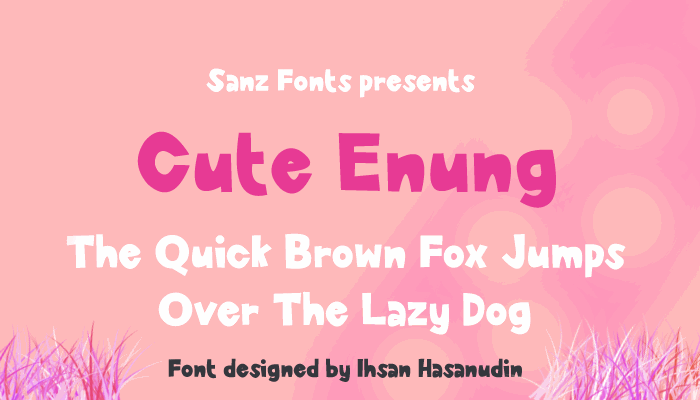
Cute Enung font – Download Grátis
A fonte “Cute Enung” é uma escolha perfeita para quem busca algo autêntico e único, que transmite alegria através do design. Inspirada no mundo encantado dos pequenos pássaros enung, essa display font traz um toque delicado e vivaz ao seu trabalho de design. A elegância natural dos pássaros enung é capturada em cada letra, proporcionando uma experiência visual que se conecta diretamente à natureza do Brasil. Esta fonte foi criada pelo designer Hamilton, e sua beleza surge da combinação perfeita de linhas curvas e traços suaves. Ela funciona maravilhosamente para nomes de marca ou produtos relacionados ao mundo infantil, animais domésticos, decoração de natal ou até mesmo elementos decorativos de uma cafeteria criativa. A “Cute Enung” é uma escolha ideal tanto para aqueles que querem dar um toque especial à sua identidade visual quanto para quem busca criar algo autêntico e memorável. Com esse design único, você poderá destacar-se no meio da multidão e oferecer aos seus clientes ou leitores a experiência de uma fonte de verdade, capaz de capturar olhares e emoções.